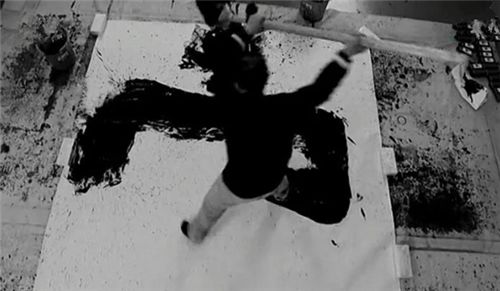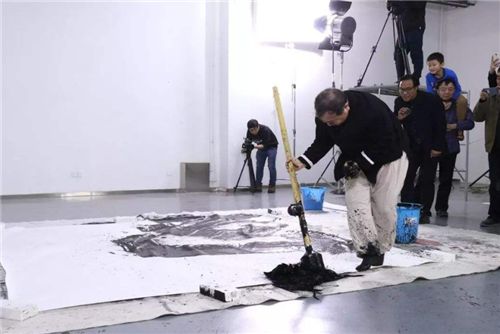
“吼书大师”因书法靠吼走红,字体被网友痛批,专家:已录入字库
在前不久,网上曾公布出一条视频,视频中身穿古典白衫的中年男子,居然拿着一杆毛笔,闭着眼睛写“学法”,说是追求“意境”,旁边还不断有人附和着说好!好!好!结果一写完,大家都被整蒙了,这不就是乱涂乱画了一气吗?甚至还出现了“射墨”派,不少网友都感叹,现在的艺术门槛真是越来越低了,遍地都是“大师”。
书法是中国传统艺术中最为传神的艺术隗宝,包括执笔、运笔、点画、结构、布局(分布、行次、章法)等内容都有极大的讲究。运笔中锋铺毫;点画意到笔随,润峭相同;结构以字立形,相安呼应;分布错综复杂,疏密得宜,虚实相生,全章贯气才是佳品。
而在书体上,重要有篆书、燕书、隶书、楷书、行书、草书,离我们生活最近的是楷书和行书,但是无论其中的哪一种书体,都有一定的章程,人们可以很直接的在其中获得审美情趣,以及一些学习与借鉴的地方。
但是现如今经常在网上露面的一些:“大师”作品,却实在是令人难以接受了,其中还有一位名气不小的书法家,名叫曾翔,他是现任中国书法院办公室主任,还是,北京大学、清华大学国书法家协会培训中心,等16所大学的特聘教授。
虽然曾翔的头衔很多,但是真正让他走红的却是他别具一格的“吼书”,从名字上就能看出,吼书就是一边吼叫,然后一边以相当狂放的姿态写书法,而且写书法的工具不是寻常的毛笔,而是一个类似于“拖把”的工具。
曾翔在写“吼书”的时候,是没有章程可以讲,他会把自己整个人都融入到纸上,然后拿着拖把一样的笔走来走去,每完成一笔都会大声的吼叫一声,有的时候写完一幅字之后,喉咙嘶哑了,还出了一身汗,连裤子上都沾满了墨水。
最后写出来的字可以料想得到了,有的笔墨很重,基本上看不出笔锋和结构。在重笔之外还有,很多淅淅沥沥滴落的墨汁,看到被墨水印上去的脚印也不用奇怪,总之常人根本看不懂写的是什么字,如同抽象艺术。
虽然曾翔凭借他的“吼书”成功走红了,但是很多看不懂又心直口快的网友就很直接的评判他的字丑,甚至说是信手涂鸦出来的,已经完全脱离于所有传统书法体。曾翔自己却解释说:“一个书法家,首先要是一个汉字的设计家。”
但是曾翔的文字还是有很多人欣赏的,欣赏他的人都称他的书法为“曾翔字体”,其中还有一款被收入到了汉仪字库中,这款字体正是“汉仪曾翔禅趣”,这种字体被大赞灵活多变、天真质朴、动感活泼,富有真趣味。不过也有人说,这种字体歪歪扭扭,就像是小孩子写的,完全降低了书法的门槛,一味的追求“不同”,而抛弃传统,真的是正确的吗?搜字体